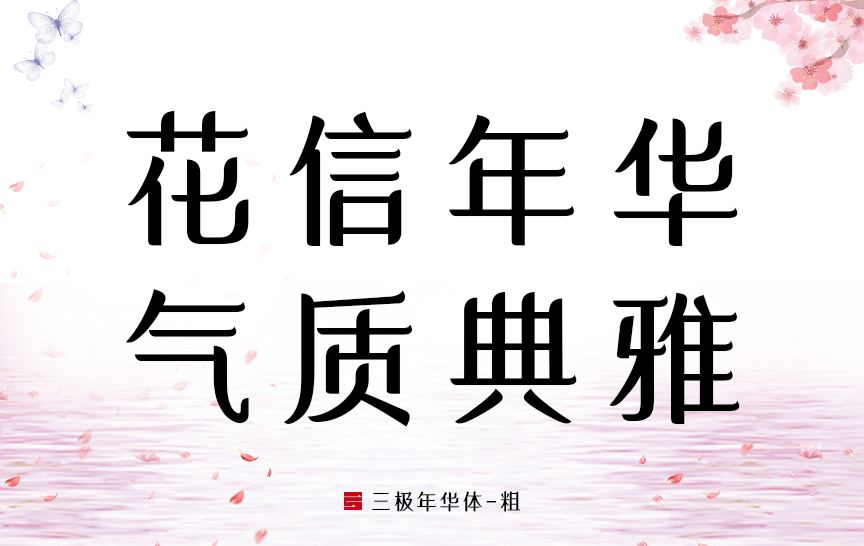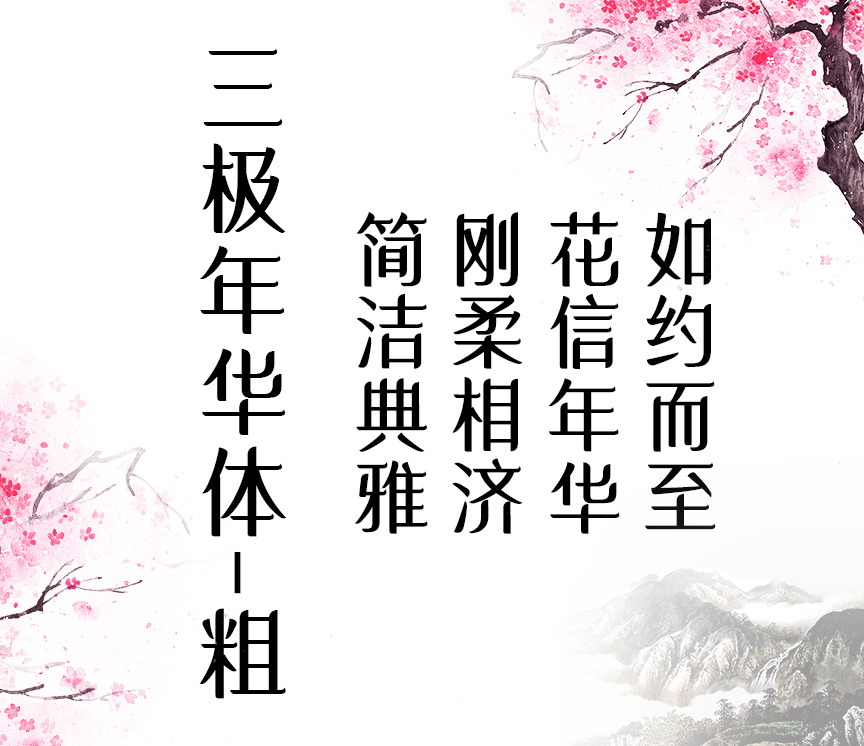
字体名称:三极年华体-粗
设计师:王荣诚
三极年华体是具有典雅气质的风格化黑体作品。兼具了黑体的简洁和宋体的雅致特征。 整体字形方正,刚柔相济,优雅大方。其横竖笔画横纵,横竖笔画粗细反差较大,加以弯钩柔美曲线点缀,突显典雅之风格。适用用于商业广告、书刊出版、产品包装及界面设计标题,店招牌匾。
适用媒介:书籍、报纸、杂志、广告、标志、宣传册、包装、店招、屏幕显示、交互设计。